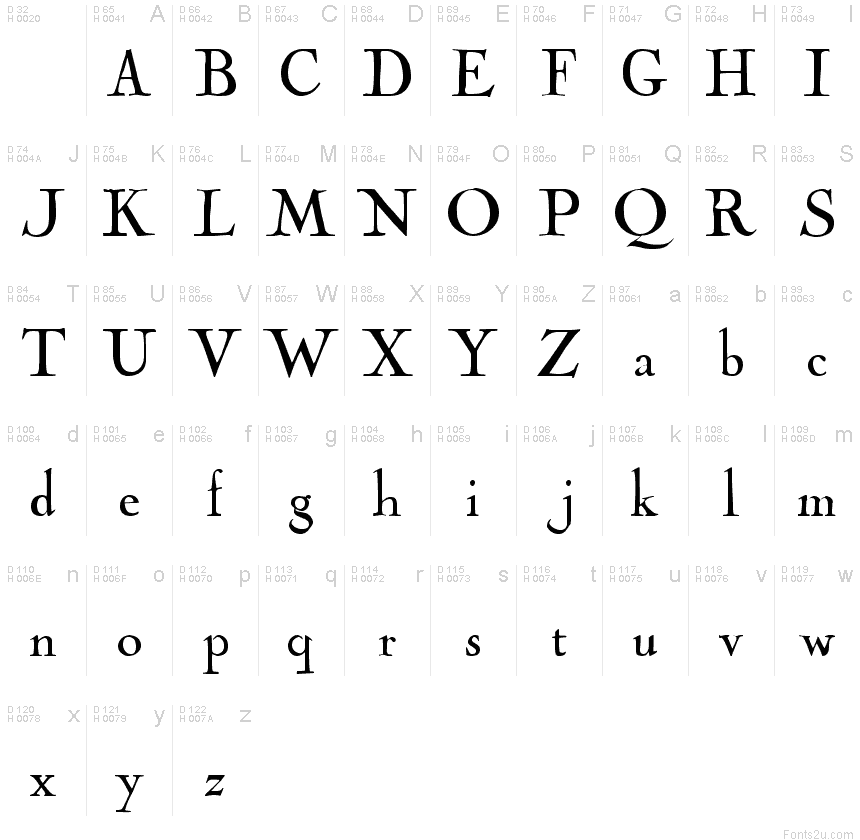
CochinArchaic autorstwa Davida F. Nalle to darmowy krój szeryfowy, który wygląda, jakby został wyjęty prosto ze starego, zniszczonego pergaminu. Litery są smukłe i lekko nieregularne, z "atramentowymi", szorstkimi krawędziami, które sprawiają wrażenie druku ręcznego, a nie cyfrowego, nadając tekstowi natychmiastowe poczucie upływu czasu i subtelnej dramaturgii.
Ten darmowy font świetnie sprawdza się na okładkach książek fantasy, w tytułach filmów kostiumowych, plakatach muzealnych, etykietach win, opakowaniach produktów rzemieślniczych czy nagłówkach blogów historycznych. Użycie CochinArchaic w nagłówkach i zestawienie go z czystym, nowoczesnym krojem bezszeryfowym w mniejszych rozmiarach zapewnia czytelność, zachowując jednocześnie sugestywny, staroświecki charakter tego pisma.